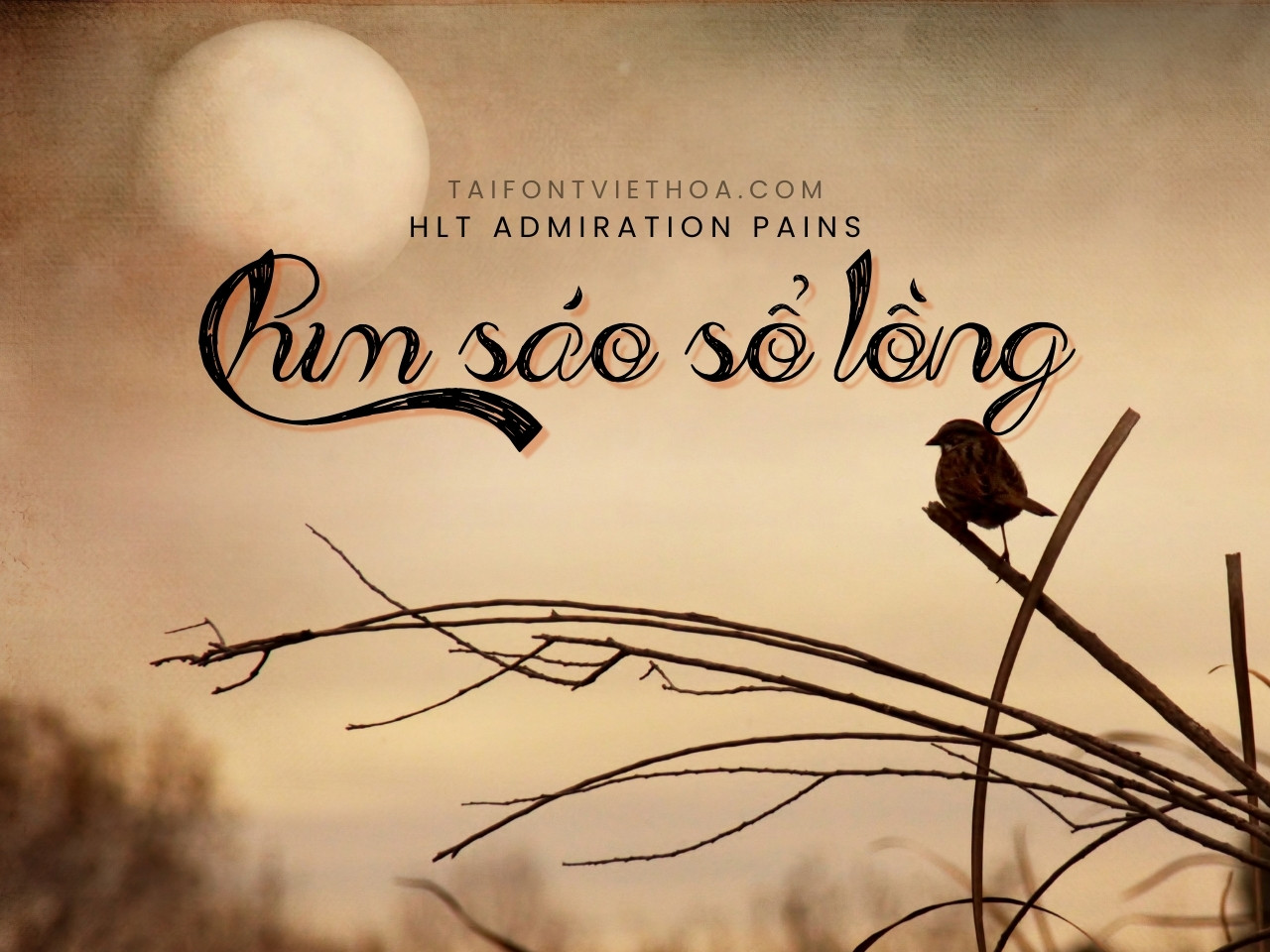
Font việt hóa HLT Admiration Pains
Giới thiệu về font HLT Admiration Pains – Tình cảm, lãng mạn và đầy nghệ thuật
HLT Admiration Pains là một kiểu chữ viết tay mang hơi thở lãng mạn, được nhóm HLT Việt hóa để hỗ trợ đầy đủ tiếng Việt cùng hơn 90 ngôn ngữ khác trên thế giới. Kiểu font này ban đầu được thiết kế theo phong cách handlettering hiện đại, kết hợp yếu tố calligraphy và viết thư pháp mềm mại. Mỗi ký tự đều được chăm chút với độ nghiêng tinh tế, nét uốn lượn uyển chuyển nhằm tạo nên cảm xúc sâu lắng trong từng dòng chữ.
Chi tiết thiết kế và ứng dụng của font HLT Admiration Pains
HLT Admiration Pains nổi bật với nét chữ thanh mảnh, nhẹ nhàng nhưng vẫn giữ được sự cân đối giữa các ký tự. Đặc trưng với các nét viết tay mềm mại, độ uốn cao, nhiều glyphs thay thế (alternates) và hỗ trợ ligatures giúp font trở thành lựa chọn lý tưởng trong những thiết kế cần yếu tố thẩm mỹ bay bổng và riêng biệt.
Ứng dụng điển hình của font bao gồm: thiết kế thiệp cưới, thư mời sự kiện, tiêu đề blog thời trang, bìa sách lãng mạn, bảng tên thương hiệu hoặc các sản phẩm in ấn mang cảm xúc như album ảnh, chữ ký cá nhân. Font này đặc biệt phù hợp với các ngành nghề thiên về nghệ thuật, thời trang, cưới hỏi và sáng tạo nội dung.